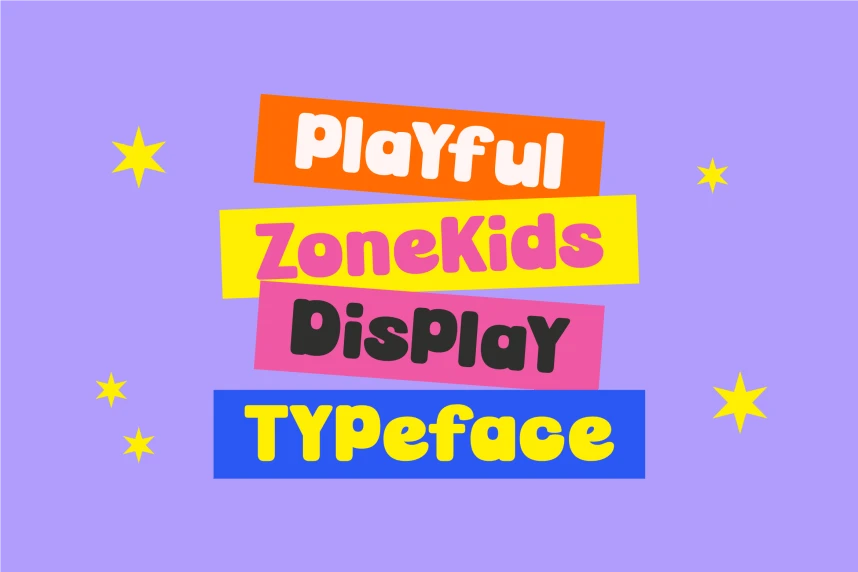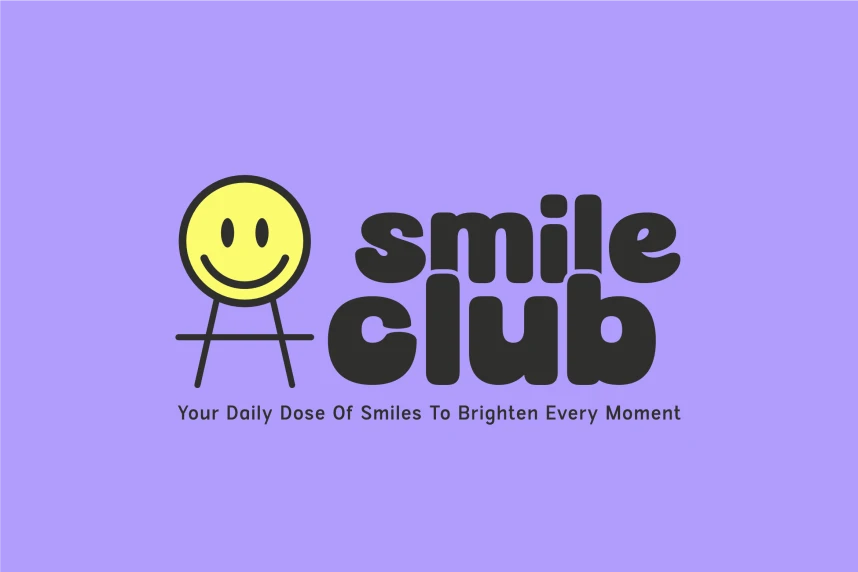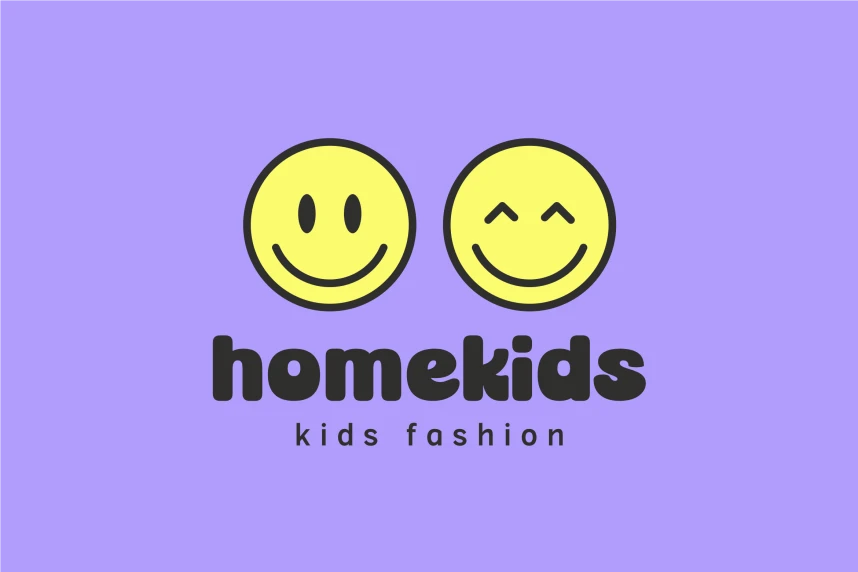
Bingbam Font - Bingbam Display ile tasarımlarınıza hayat verin; dikkati anında çekmek üzere tasarlanmış, cesur ve eğlenceli bir yazı tipidir. Kalın hatlı harf biçimleri, yuvarlak köşeler ve neşeli bir kişiliğe sahip olan bu yazı tipi, çocuklar için projeler, çizgi filmler, marka oluşturma, afişler,
Bingbam Font - Bingbam Display ile tasarımlarınıza hayat verin; anında dikkat çekmeyi amaçlayan cesur ve neşeli bir yazı tipidir. Kalın harf formaları, yuvarlak köşeler ve neşeli bir kişiliğe sahip olan bu yazı tipi, çocuk projeleri, çizgi filmler, marka oluşturma, afişler, ambalajlar ve sosyal medya grafikleri için mükemmeldir.